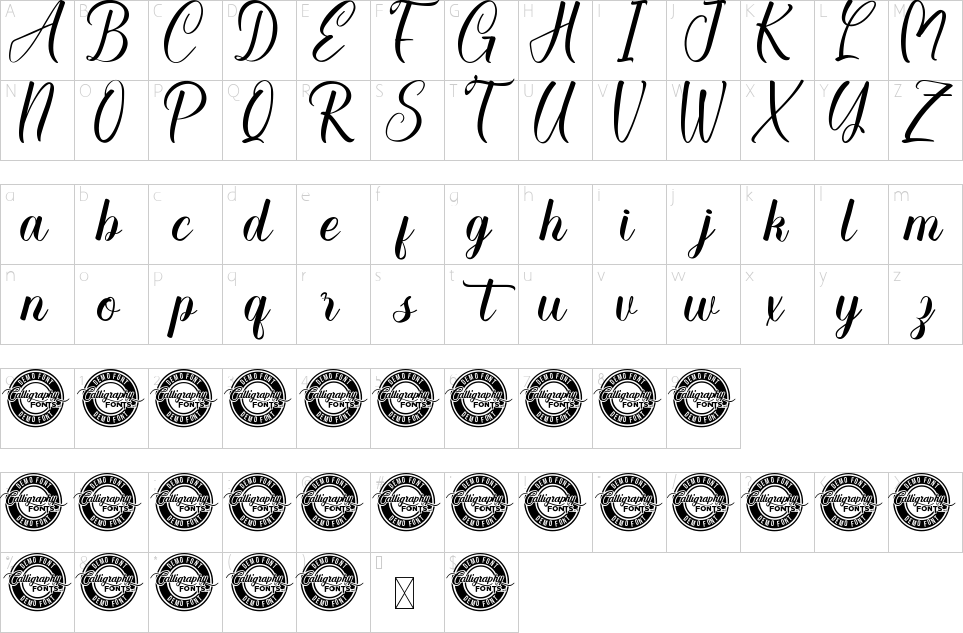
Aesthetic Stories Font – Download Grátis
A fonte Aesthetic Stories oferece um encantamento visual para estilos gráficos e design digital. Desenhada por CalligraphyFonts, esta fonte é perfeita para criações de design estético, sendo particularmente adequada para aplicativos em sistemas Windows e Mac. Com seu design minimalista e elegante, Aesthetic Stories pode aprimorar a presença visual de qualquer projeto digital. Suas linhas retas e curvas arredondadas criam um equilíbrio visual atraente, ideal para headlines e subtítulos. Aesthetic Stories tem sido baixada milhares de vezes, demonstrando sua popularidade e valor para quem busca uma fonte de alta qualidade sem custos. Download Aesthetic Stories hoje e transforme seu design digital em um trabalho de arte.